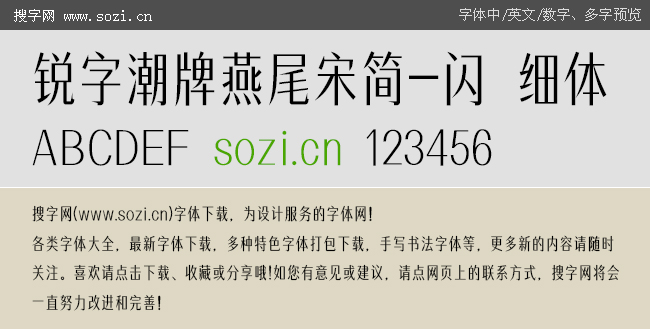
銳字潮牌燕尾宋簡-閃 細(xì)體
搜字網(wǎng)提供一款銳字潮牌燕尾宋簡-閃 細(xì)體中文字體下載,銳字潮牌燕尾宋簡-閃是一款非典型宋體字,它簡化了部分宋體字特征,橫豎筆形粗細(xì)視覺相等,整體比例拉長,字形看上去挺拔、俊秀、優(yōu)雅,字體內(nèi)部空間松緊度均勻,合理的留白安排給人以視覺上的輕松感受,精致而透氣。從而呈現(xiàn)出一種更加簡約、更具現(xiàn)代感的宋體字。用于標(biāo)題設(shè)計(jì)、海報(bào)設(shè)計(jì)、包裝設(shè)計(jì)等場(chǎng)景廣泛應(yīng)用。(本字體為個(gè)人非商用版,商用請(qǐng)聯(lián)系作者購買授權(quán))